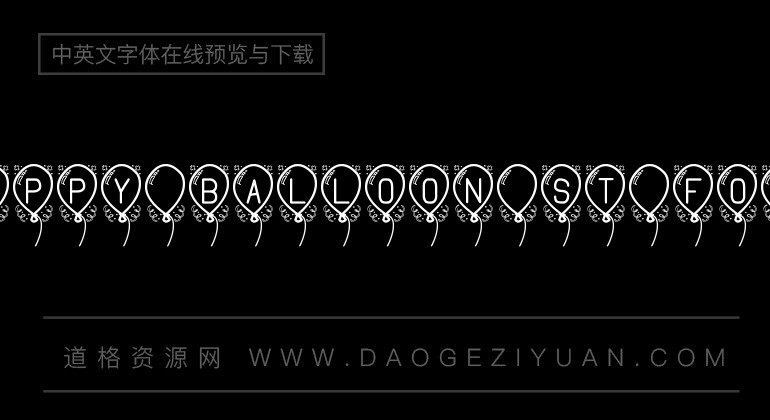
Happy Balloon St Font 是一种手写风格的字体,其特点是轻快、活泼、多彩。它的字母呈圆滑的气球形状,每个字母都有一个小气球形状的装饰部件。整个字体的设计非常适合用于庆祝、生日、派对、节日等场合的设计或者印刷品中,能够为作品增添一份欢乐和轻松的氛围。此字体可以在商业和非商业场合中免费使用,支持多种语言,适合用于海报、卡片、包装等设计中。内容介绍
Happy Balloon St Font是一款非常不错的手写艺术字体,具有很好的视觉感,适合于文化类的宣传设计、商业类品牌的广告和产品包装设计以及个性化文字排版等较多场景。